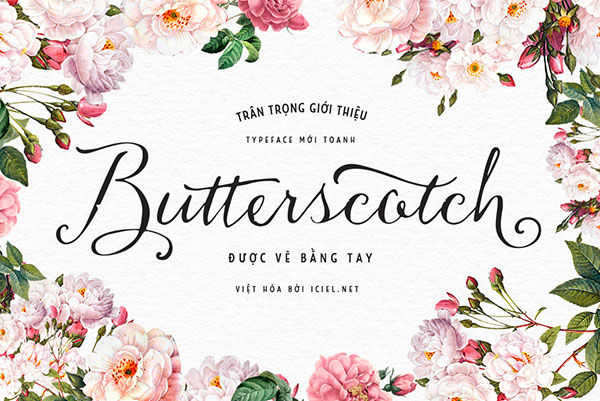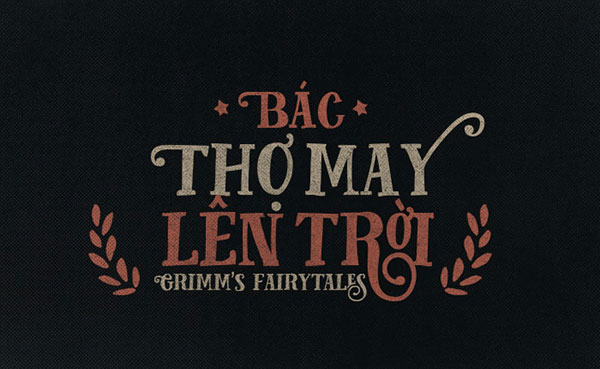
1. Giới Thiệu Về Font Chữ Việt Hóa Iciel
Font chữ Việt hóa từ Iciel là một bộ sưu tập nổi tiếng với các kiểu chữ được thiết kế sáng tạo, mang đậm phong cách nghệ thuật và phù hợp cho nhiều loại dự án thiết kế khác nhau. Những font này được Việt hóa chuyên nghiệp, hỗ trợ đầy đủ dấu tiếng Việt, đảm bảo chất lượng cao và thẩm mỹ.
Nguồn Gốc:
Iciel là một nhà thiết kế font chữ tại Việt Nam nổi bật với phong cách độc đáo, thường lấy cảm hứng từ các kiểu chữ cổ điển, hiện đại, hoặc các xu hướng thiết kế quốc tế.
Các bộ font từ Iciel thường được chăm chút tỉ mỉ để hỗ trợ tốt nhất cho người dùng tiếng Việt.
Đặc Điểm Nổi Bật:
Hỗ trợ đầy đủ tiếng Việt: Với các dấu câu được căn chỉnh chính xác và đẹp mắt.
Đa dạng phong cách: Bao gồm từ chữ thanh mảnh hiện đại đến kiểu chữ cổ điển, thư pháp hoặc thậm chí kiểu chữ sáng tạo theo xu hướng nghệ thuật.
Ứng dụng linh hoạt: Thích hợp sử dụng trong thiết kế poster, logo, tiêu đề, hoặc các sản phẩm in ấn và kỹ thuật số.
Lợi Ích Khi Sử Dụng:
Chất lượng cao: Mọi font chữ đều được kiểm tra kỹ lưỡng về tính thẩm mỹ và tính ứng dụng.
Phù hợp với dự án sáng tạo: Đáp ứng được nhiều loại thiết kế từ truyền thống đến hiện đại.
Font chữ Iciel Việt hóa nổi bật với các đặc điểm sau, giúp nó trở thành sự lựa chọn hàng đầu cho nhiều nhà thiết kế:
Hỗ Trợ Đầy Đủ Tiếng Việt
Tất cả font của Iciel đều được Việt hóa chuyên nghiệp, hỗ trợ đầy đủ bảng chữ cái tiếng Việt với các dấu câu chuẩn xác và đẹp mắt.
Đảm bảo tính thẩm mỹ khi sử dụng trong văn bản hoặc thiết kế đồ họa có nội dung tiếng Việt.
Thiết Kế Độc Đáo
Phong cách đa dạng: Iciel mang đến bộ sưu tập phong phú, từ cổ điển (vintage), hiện đại (modern), tối giản (minimalist) đến kiểu chữ viết tay (handwriting).
Sáng tạo và tinh tế: Các font thường mang đậm dấu ấn cá nhân, phù hợp cho nhiều chủ đề và phong cách thiết kế.
Chất Lượng Cao
Font chữ được thiết kế tỉ mỉ, chú trọng đến từng chi tiết, bao gồm khoảng cách chữ (kerning) và nét chữ (stroke).
Hình dáng chữ rõ ràng, dễ đọc, đảm bảo chất lượng khi sử dụng ở kích thước lớn hay nhỏ.
Dễ Dàng Ứng Dụng
Đa năng: Có thể sử dụng cho nhiều mục đích khác nhau như:
Thiết kế logo
Tiêu đề bài viết
Thiệp mời, poster
Các dự án thương mại và cá nhân.
Tinh Thần Văn Hóa Việt Nam
Một số font Iciel được thiết kế lấy cảm hứng từ các yếu tố văn hóa Việt Nam, tạo nên sự gần gũi, thân thuộc nhưng vẫn hiện đại và mới mẻ.